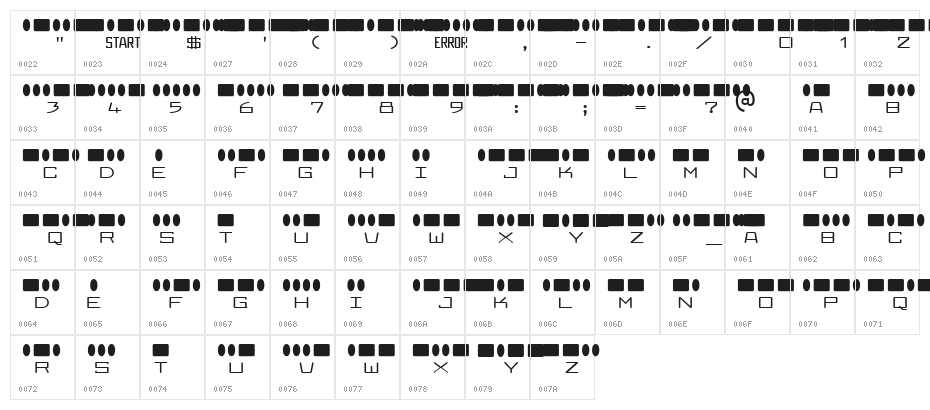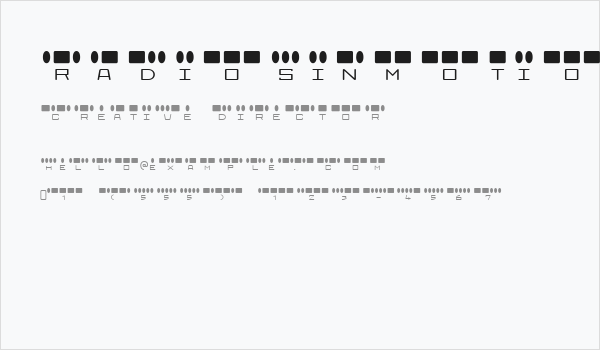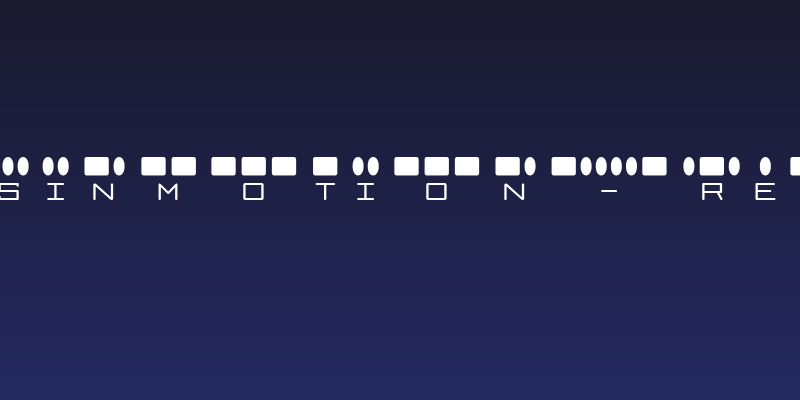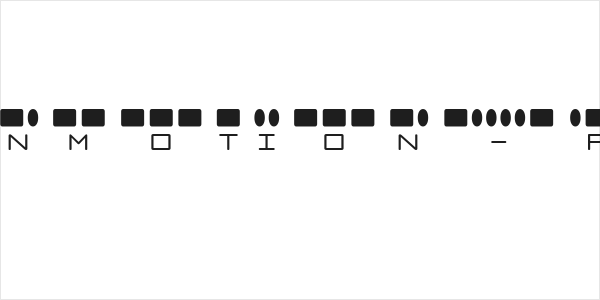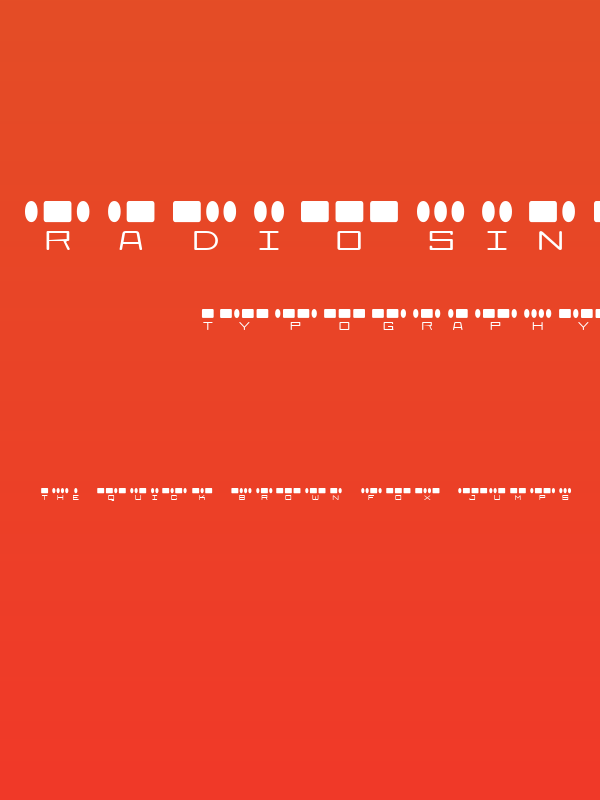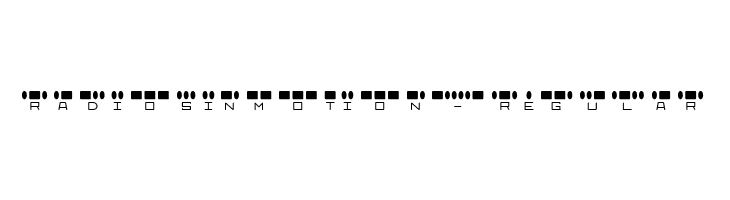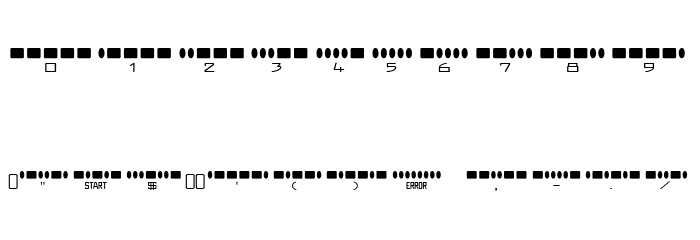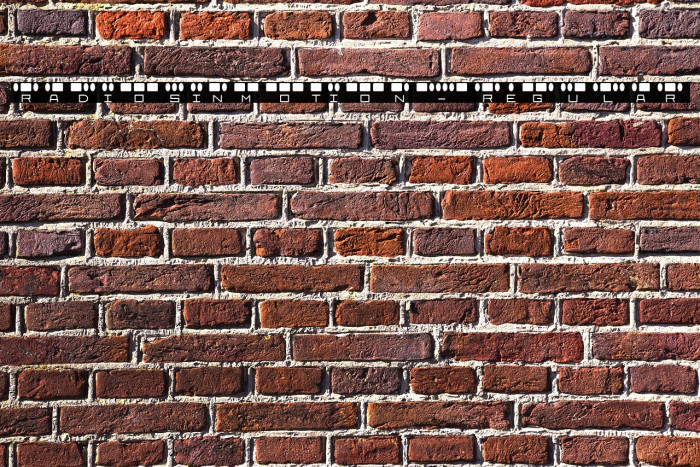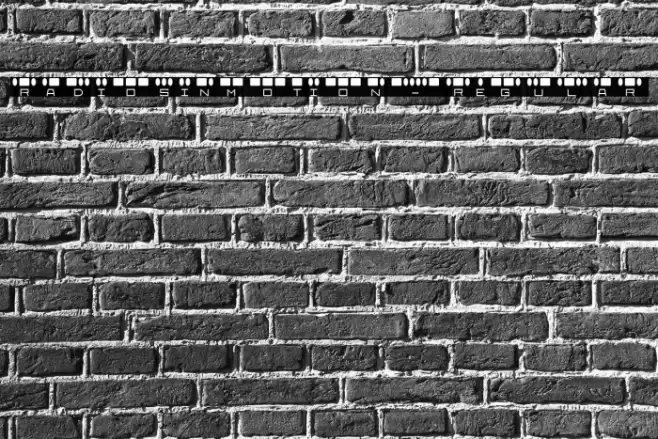
RadiosinMotion-Regular Font
| Caso de uso | Headlines, Artistic projects |
| Projetos propostos | Ideal for themed designs related to communication, technology, or historical contexts. |